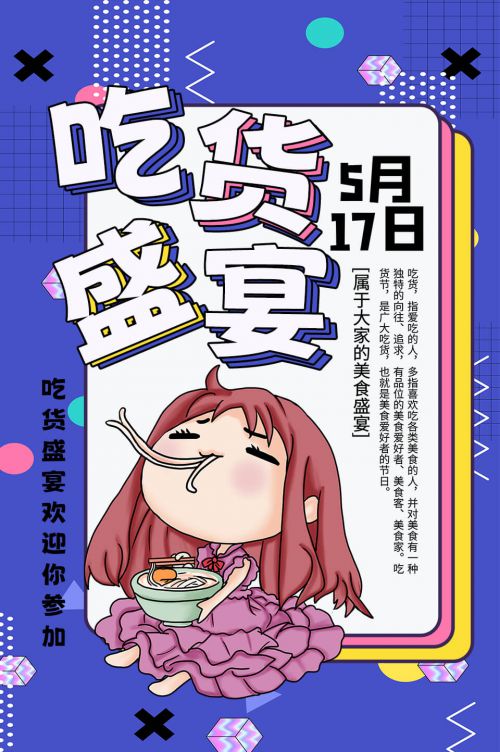
荆南波波黑
荆南波波黑是一款以卡通可爱为风格的创意字体,将童趣与实用巧妙融合,为设计场景注入鲜活生命力。 荆南波波黑字形方正饱满,重心居中稳定,中宫宽博的设计让字体兼具开阔感与亲和力,阅读时轻松无压力。笔画采用全圆角处理,搭配圆头设计,转角处的柔和弧度与断开的笔画连接方式,既保留了字体的识别性,又增添了俏皮灵动的视觉效果,宛如手绘般的亲切感扑面而来。 字重为粗体,笔画粗细均匀有力,整体造型敦实可爱,在各类尺寸下均能保持清晰的辨识度,无论是标题设计还是细节装饰,都能轻松吸引目光。 作为免费商用字体,荆南波波黑打破了设计成本的限制,广泛适用于儿童读物、包装设计、品牌LOGO、社交媒体配图、节日海报等场景。无论是打造活泼的儿童产品包装,还是设计温馨的节日宣传物料,荆南波波黑都能以其独特的卡通魅力,为作品注入温暖有趣的视觉灵魂,成为设计师传递快乐与创意的得力工具。